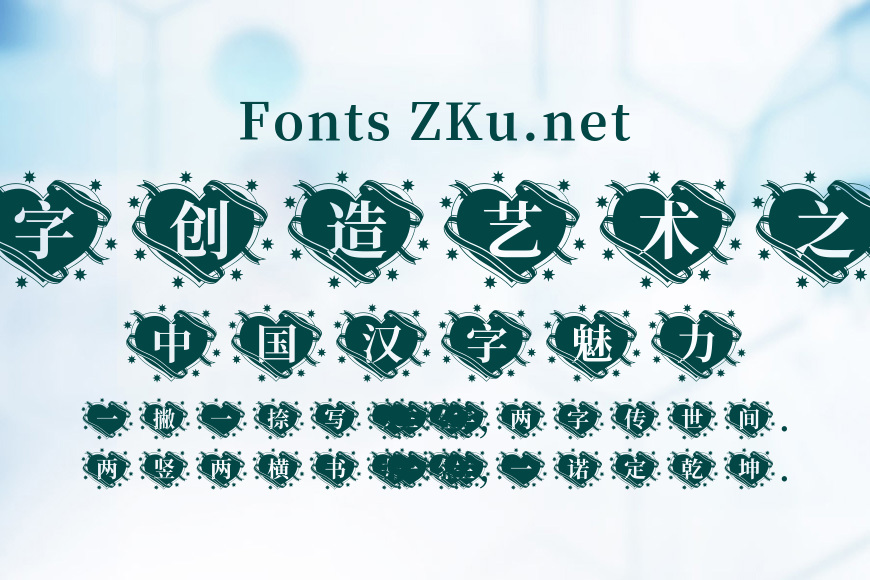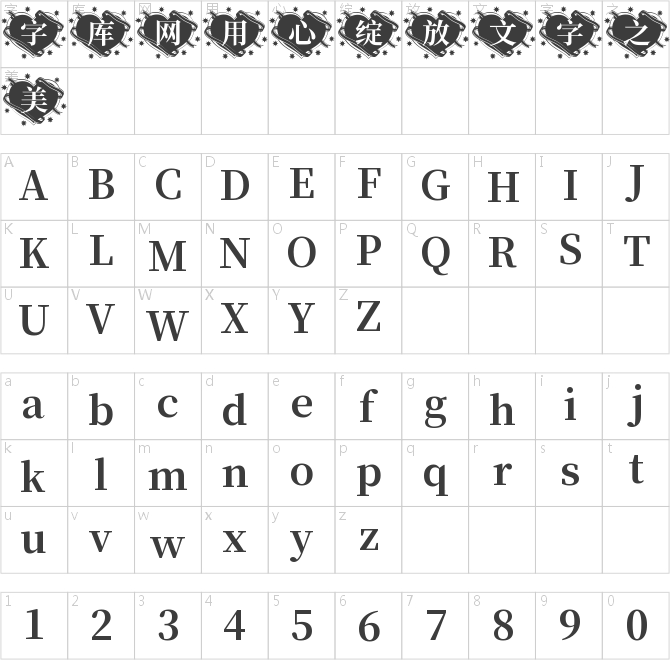
思源宋体花样心纹
这个字体是在“思源宋体 粗体”基础上提取英文与符号共123个字形,汉字6763个常用字修改而成,所谓花样字体,笔者自定义为:给常规字形加一些修饰花纹效果。本次共享的花样字体只对6763个汉字添加花纹,英文与符号保持原字形不变,大部分花样字体并不适用于大篇幅的文章使用,主要作用于标题或一些特殊场合,如图片水印等等。